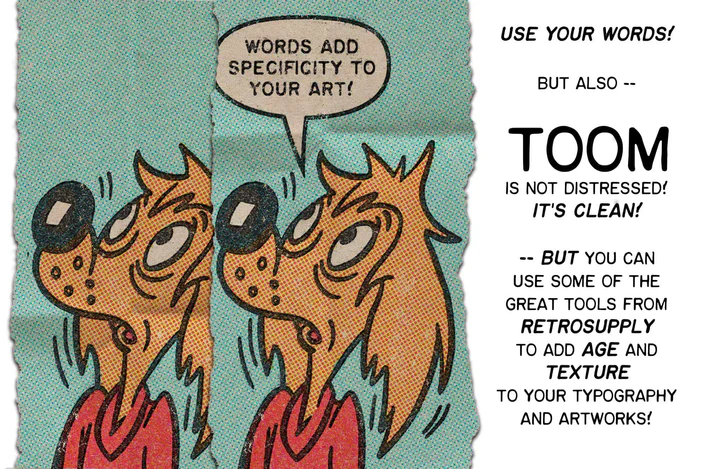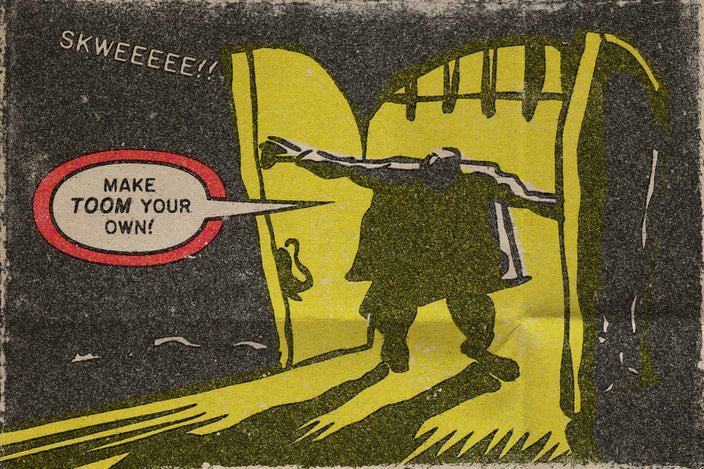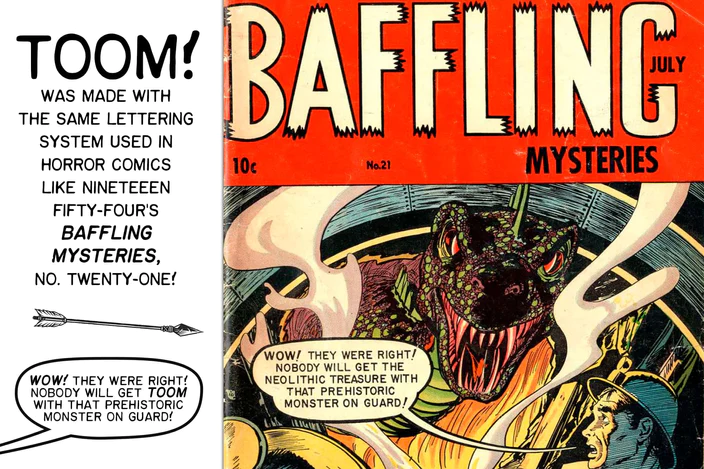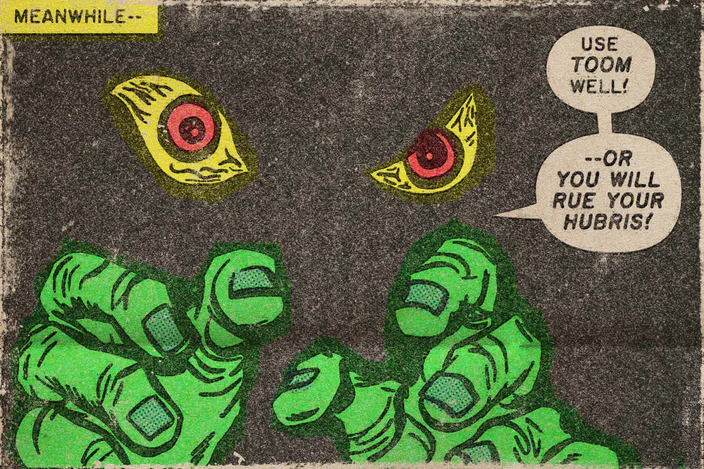
Nhà xuất bản truyện tranh kinh dị những năm 1950 EC Comics đã làm một điều gì đó tinh tế và rùng rợn.
Họ đã sử dụng một chiếc máy để mô phỏng chữ viết tay một cách máy móc. Hệ thống chữ Leroy mô phỏng hình thức chữ viết tay nhưng có tính nhất quán vô hồn.
Hãy tưởng tượng việc xuất bản trên máy tính để bàn nhưng trên một thiết bị ọp ẹp và có những mâu thuẫn nhỏ.
Giờ đây, bạn có thể ghi lại vẻ cổ điển rùng rợn tương tự với TOOM — phông chữ mới của chúng tôi do nghệ sĩ, nhà văn và giáo sư đại học Christopher Sperandio thiết kế.
- 3 mặt viết hoa toàn bộ (Regular, Italic, Bold Italic).
- Các tính năng bổ sung như đầu lâu, dòng phấn khích và ký tự in sai.
- Được thực hiện bởi nghệ sĩ, nhà văn và giáo sư đại học Christopher Sperandio.
Gần đây, tôi thấy mình cần một phông chữ mới cho tiểu thuyết đồ họa mới của mình, vì vậy tôi đã tạo một phiên bản kỹ thuật số của Hệ thống Chữ Leroy. Những người hâm mộ truyện tranh cổ sẽ nhận ra Leroy Lettering. Bill Gaines, nhà xuất bản của EC Comics, đã thuê Jim Wroten, cựu nhân viên bán hàng của Leroy Lettering System, và vợ ông, để gửi thư cho TẤT CẢ sách của họ. Việc sử dụng Leroy Lettering đã làm cho sách EC trở nên khác biệt.
Phông chữ tôi tạo ra có tên là TOOM, tên của nó là sự kết hợp giữa TOON và TOMB, nhằm tôn vinh việc sử dụng chính Hệ thống Chữ Leroy trong truyện tranh kinh dị những năm 1950.
Kể từ khi tạo ra phông chữ này, tôi đã sử dụng nó trong các tiểu thuyết đồ họa mới của mình và những đóng góp của tôi cho các tuyển tập truyện tranh như š! từ kuš! komiksi có trụ sở tại Riga, Latvia và Kutlul, có trụ sở tại Berlin và Rotterdam, cũng như trong truyện tranh hàng ngày mà tôi tạo và đăng trên Instagram.